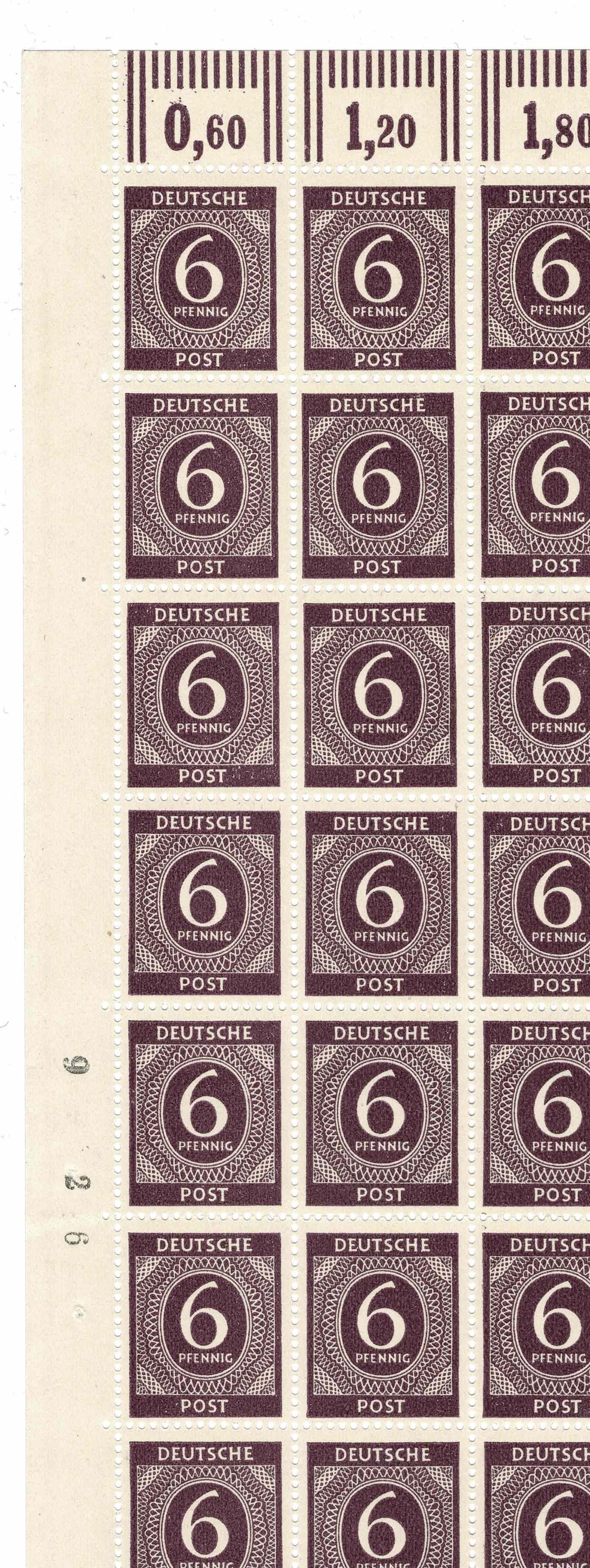
Welche Schrift ist das? (Briefmarkenbögen)
ich bin Briefmarkensammler und sammle Bögen der I Ziffernserie.
Diese Serie wurde nach dem II W Krieg durch die Alliierten in's Leben gerufen. Sie war nur eine kurze Zeit von ca 1946 bis 1948 im Verkehr. Diese Marken wurden im Plattendruck und im Walzendruck (Rotationsdruck) erstellt. Mich interessiert der Walzendruck.
Charakteristisch an diesen Bögen ist, dass sie oben und unten am Bogenrand Streifen aufweisen. Die Bogen wurden durch die Druckmaschine der ehemaligen Reichsdruckerei auf den Maschinen MI bis MIII geruckt. Alles Rotationsdruckmaschinen. An den linken und rechten Seitenrändern wurden sogenannte Bogenzähler durch ein Paginierwerk aufgedruckt.  Wir überlegen in der Sammelgruppe wie die Schrift dieser Zahlen heißt. Wäre diese Schrift definiert, können evtl. verschiedene Druckmaschinen unterschieden werden oder und es gäbe eine einheitlichere Ansicht über dieses Thema.
Ich kann Deine Antwort nicht einordnen. So jetzt habe ich es "Clarendon" ist eine Schrift.
Wikipedia weiß es: "Die Clarendon kam in Deutschland 1850 von der Bauerschen Schriftgießerei auf den Markt. 1953 wurde sie von Hermann Eidenbenz überarbeitet und von Linotype veröffentlicht.[2] Sie besitzt einen zeitlosen Stil, durch den sie vielfältige Verwendung findet und immer wieder gerne aufgegriffen wird."
Die Jahreszahl 1850 kann gut sein, da schon Germania-Marken und Inflations-Marken Bogenzähler in dieser Art hatten.
Solche Paginierwerke hatten normalerweise keine bestehende Satzschriften 1:1 verwendet, sondern die Form der Ziffern daran angelehnt und nach technischen Kriterien (Haltbarkeit, Radien, Tintenfallen etc.) für den Einsatz als Paginierstempel optimiert.